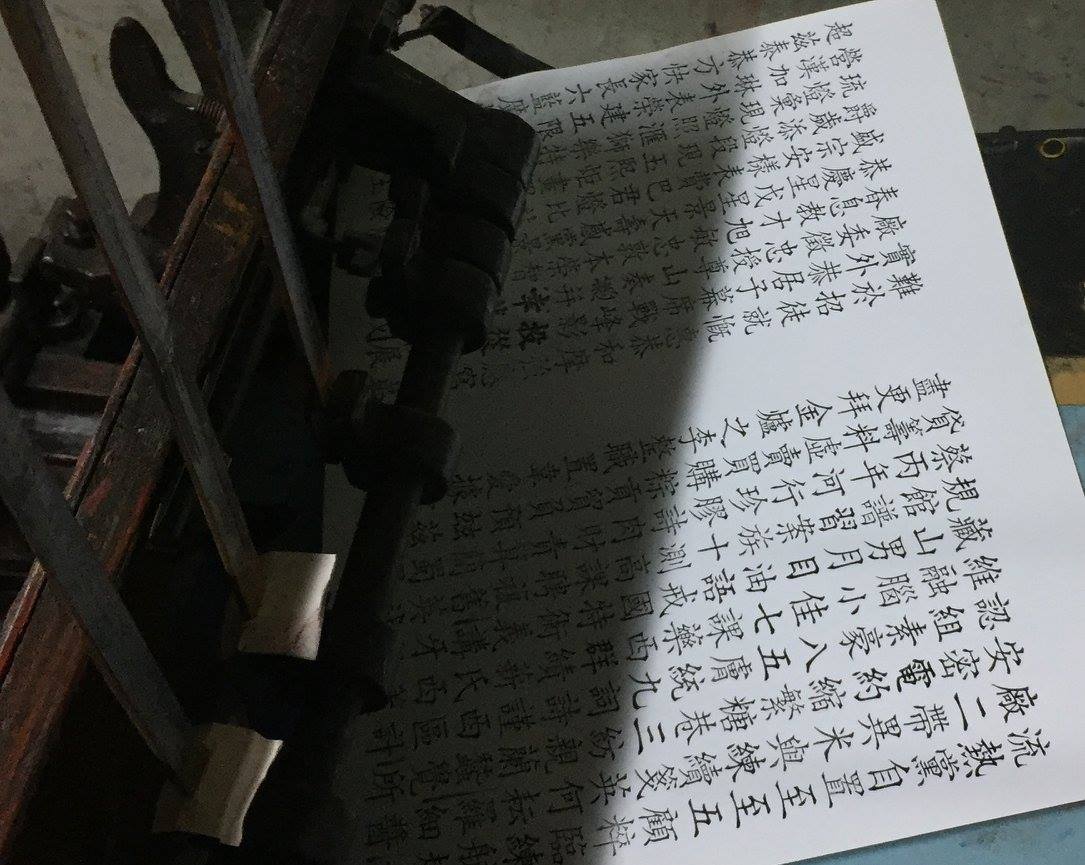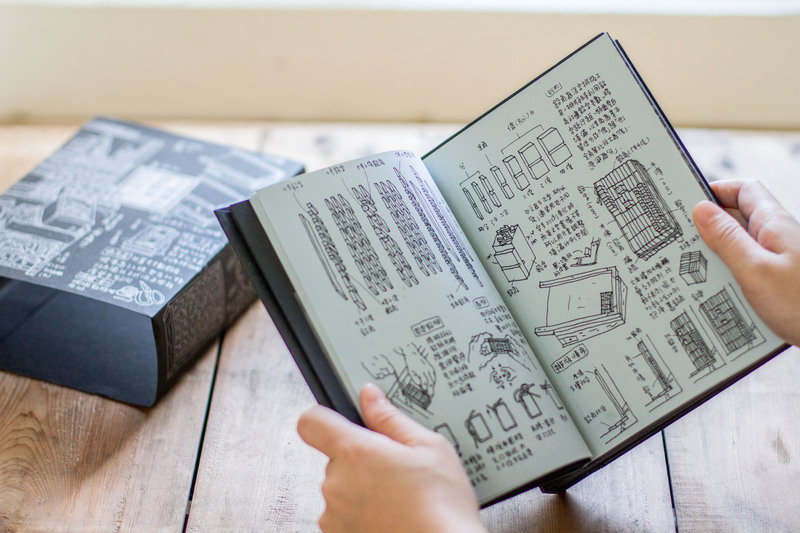
初夏渐至,端午临近,TypeTour 文字设计与视觉文化旅行又将出发!
此次我们将从台南启程,踏访古都遗迹,探索台南最大的铸字厂与印刷博物馆,走老街,串小巷,体味「台南过生活」;随后前往繁华而现代的的台北,街头漫游「猎字」识城,在日星铸字行和铁皮刻字铺与老板促膝而谈,到只闻其名的字体公司和设计工作室内部打探一番……旅人视角所看不见的城市文化,TypeTour 将带你深入了解。
TypeTour 与普通的主题旅游项目不同,我们希望聚集更多对字体排印、平面设计、视觉文化感兴趣的朋友们,在旅行的同时促成更有价值的交流。每次字体旅行,我们都将在保证行程完成度和质量的前提下,留出充分的自由活动时间,让参与者拥有更多自主探索的机会,领队也会根据团员的需求,给出针对性的建议。
内容简介
- Day 1(6/13,周三):上海–高雄–台南;安平古堡
- Day 2(6/14,周四):糖福印刷创意馆(台湾最大印刷博物馆);与阿之宝铅字字体数字复刻计划项目小组交流
- Day 3(6/15,周五):前往嘉义;丰益印刷(南部最大铸字厂);晚上抵达台北
- Day 4(6/16,周六):日裕印刷;日星铸字行;柏祥号铁皮字铺
- Day 5(6/17,周日):justfont 字体公司;卵形工作室;自由活动
- Day 6(6/18,周一):抵达新北;文鼎字库;淡水老街自由活动
- Day 7(6/19,周二):自由活动,返回
(行程可能根据实际情况作前后调整。)
详细行程
DAY 1
安平古堡 又名「热兰遮城」,最初由荷兰人建于 1624 年,是台湾最早的要塞建筑,也是是荷兰人统治台湾全岛和对外贸易的总枢纽。1662 年郑成功取城后建立了第一个汉人政权,之后改城名为安平;到了清代,安平城逐渐没落倾颓,日据时期则改建为日式海关宿舍与红砖平台。安平古堡象征着台湾早期的城市发展史,是了解台湾汉族文化发源的重要古迹。
DAY 2
糖福印刷创意馆 前身为成立于民国 43 年的「糖福印刷所」,系台糖公司为印制内部文件而成立。随着印刷技术的进步,铅字活版印刷逐渐被淘汰,而糖福仍保留了全台唯一一套最完整的活版印刷机具,百万粒颗字,八万多颗铜模,大量的零件铅块和锌板,以及年代久远的印刷制品,见证了台湾活版印刷的辉煌时期。
阿之宝交流 阿之宝是专业设计公司,关注、研究、策展推广台湾传统活版印刷文化超过十年。2015 年以活字排版为灵感设计的「字田・活印盒」受到大众喜爱,并连获国内外设计大奖。隔年续推的众筹项目「老师傅的排版桌」募得金额超过百万台币,并获金蝶奖肯定。目前阿之宝正全力投入「台湾铅楷体・数位化计划」。
DAY 3
丰益印刷 丰益印刷曾是台湾南部最大的铸字厂,印厂前身为民国 32 年创立的「罗印务馆」,后迁到新荣路现址。民国 50 年至 70 年生意达到颠峰,生意的盈余用来添购铸字机具和器材,光是购置不同字体的铜模,成本就足矣买下当年一条街。如今库藏中拥有六十多年历史的铸字机仍能使用。
DAY 4
日裕印刷 台北市万华地区曾是台湾报业的聚集地,300 多家活字印刷厂的大本营。时过境迁,中南等大铸字厂纷纷关闭。目前位于万华区西门町永福街巷的「日裕印刷」,年逾古稀的老板林金仁年轻时曾是报社检排部的领班,退休前创办印刷所,营运至今。全盛时期的印所与十几家周季报刊业务往来繁忙。我们将参观所内保存的中英铅字、印刷品藏品和排版工具,听林老板分享从业经历和活字排版的经验。
日星铸字行 成立于 1969 年的日星铸字行,专门生产金属活字,以提供给印刷行业。中南铸字厂于 2000 年关闭后,日星铸字行成为台湾唯一仅存的金属活字工厂,厂内库藏三十余万字的中文铅体与字模。四十余年不间断,以火铸造铅字,在光与电的现代社会中,守护属于台湾的遗产。同时,日星铸字行与中央研究院数位文化中心合作,耗时两年多,成功把堪称华人世界最后一套的「繁体中文铅字字体」数字化,成立专属网站、做成字型档提供给民众下载,命名为「日星初号楷体」,也使得日行铸字行成为台湾字体文化交流重要的平台。
柏祥号铁皮字铺 柏祥号刻字铺从日治时代开业至今已经是第三代,铁皮刻字就是在铁皮上用凿子将铁皮依照设计的字型挖空,再以喷漆将凿出的字型显现在物体上。早期贸易繁忙的年代,这项技术曾经广为应用与茶行货箱的信息喷涂中。在大稻埕早期凡是有货物要出口,这些公司行号就会向柏祥号刻字铺下单。随着时代与环境的变化,喷字需求大幅下降,柏祥号成为大稻埕目前仅存的刻字铺,在民乐街巷弄中默默守护逐渐失传的工艺。往期 TypeTour 中,几乎每一位去过柏祥号的团员都会请老师傅亲手打一块刘体楷书或镂空西文的铁板留作纪念。
DAY 5
justfont & 字恋小聚 justfont 是世界最先进的中文云端字型应用,也是华文第一个推出「中文网路字型(web font)服务」的网站。团队以改善台湾的中文字型产业为愿景,致力于推广台湾的字体排印学学,深耕和推广字体排印学各种知识汇整相关材料、师资。「字恋小聚」是 justfont 每月固定举办的在活动,广邀相关专业人士、字体爱好者参与每次不同主题的字体相关议题讨论、讲座或工作坊。 TIB TypeTour 团员将与在地社群共同参与字恋小聚,谈谈如何从字体去看城市属性,异化彼此熟烂的生活场域,交换两地文字风景。
卵形工作室 卵形平面设计工作室,成立于 2015 年,主理人叶忠宜。三年前在当时的台湾堪称「Typography 的沙漠之地」之时,叶忠宜策划引进并翻译知名字体设计师小林章的数本著作《字型之不思议》、《欧文字体 1:基础知识与活用方法》、《欧文字体 2:经典字体与表现手法》、《街道文字》,是台湾「字体热」产生的关键一环。而后开始从谈版权、统筹、改版方向、到整个设计一路亲自操刀到底,制作了日本字体设计专业杂志《TYPOGRAPHY 字誌》的繁体中文版,是华语圈第一本字型 Mook,通过实际努力对台湾设计界生态起到了重要改善作用。
DAY 6
文鼎科技 文鼎科技成立 25 年来,致力于各国语系字型的设计及字型相关技术的开发,提供企业及个人全方位字型解决方案。历经字体产业风起云涌,也见证了因为盗版而凋零的年代,是台湾本土过去二十余年,坚持到现在的两家字体厂商之一。文鼎科技凭借着丰富的经验与优秀团队,致力于中文字体的设计,二十六年来开发上百套中文字体,为提供用户最佳的视觉体验效果。其招牌产品「晶熙黑体」于 2013 年从 6,000 余件商业作品中脱颖而出,获得《Good Design Award》BEST 100 大奖,该套字型更是为 2016 年蔡英文竞选团队所采用。
DAY 7